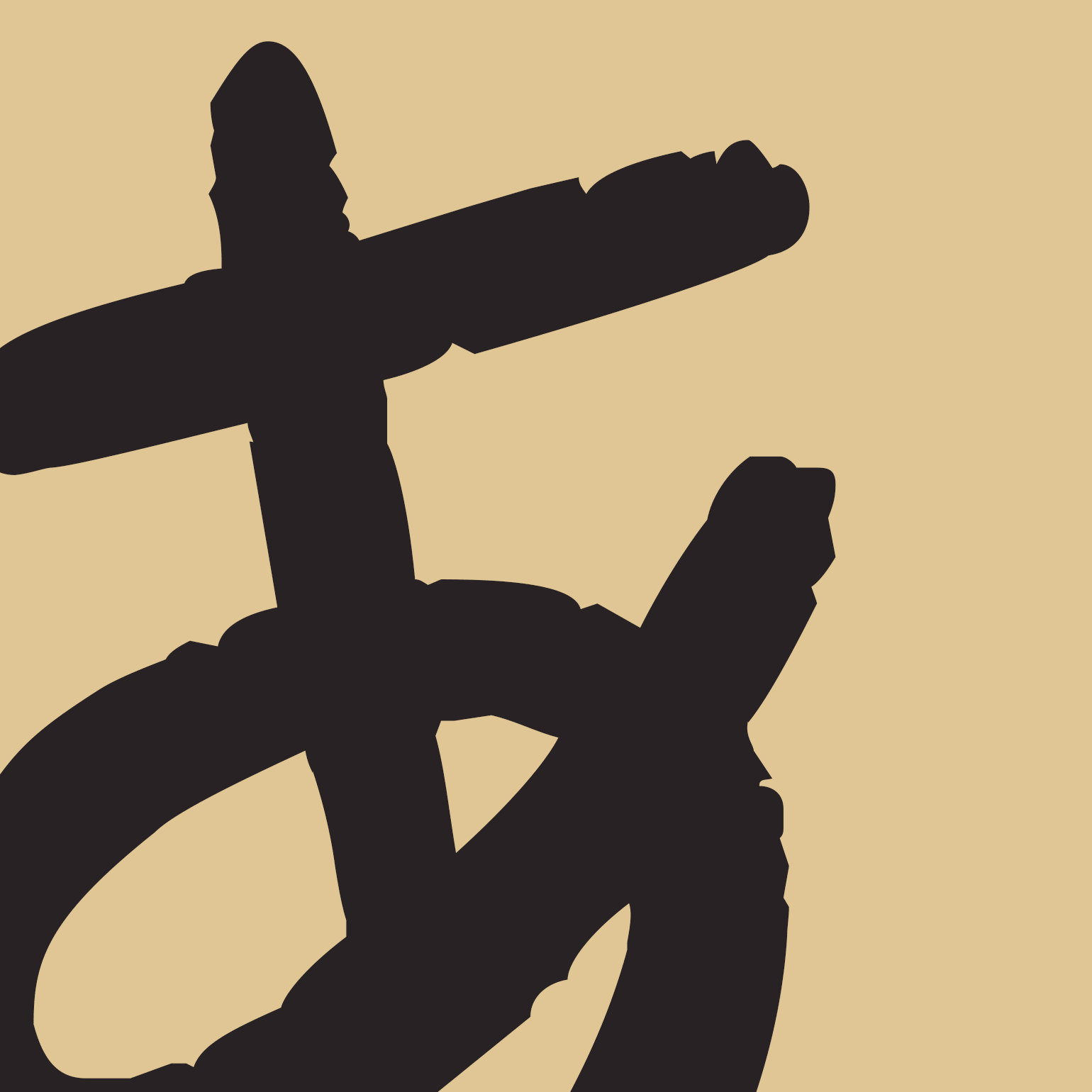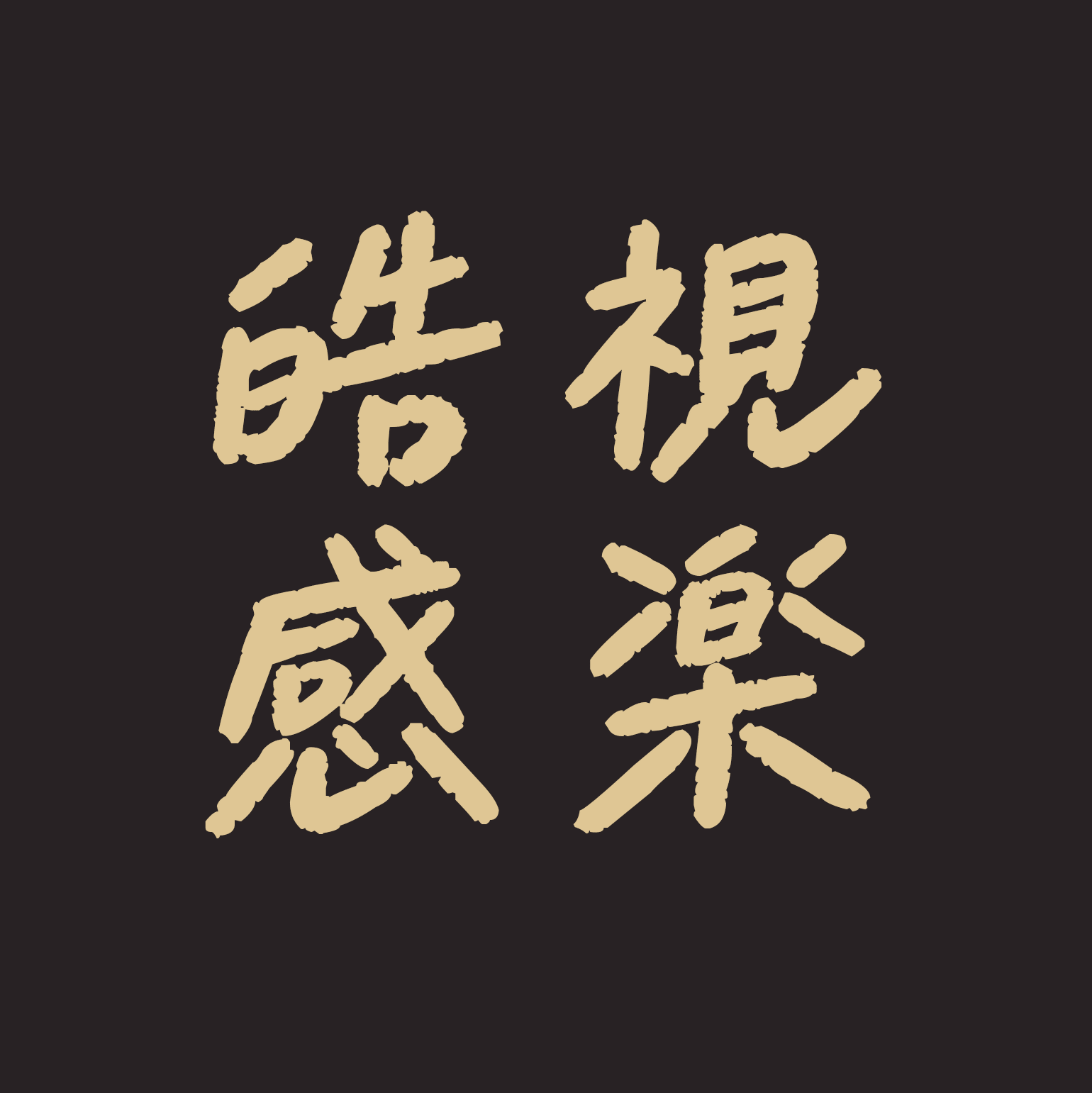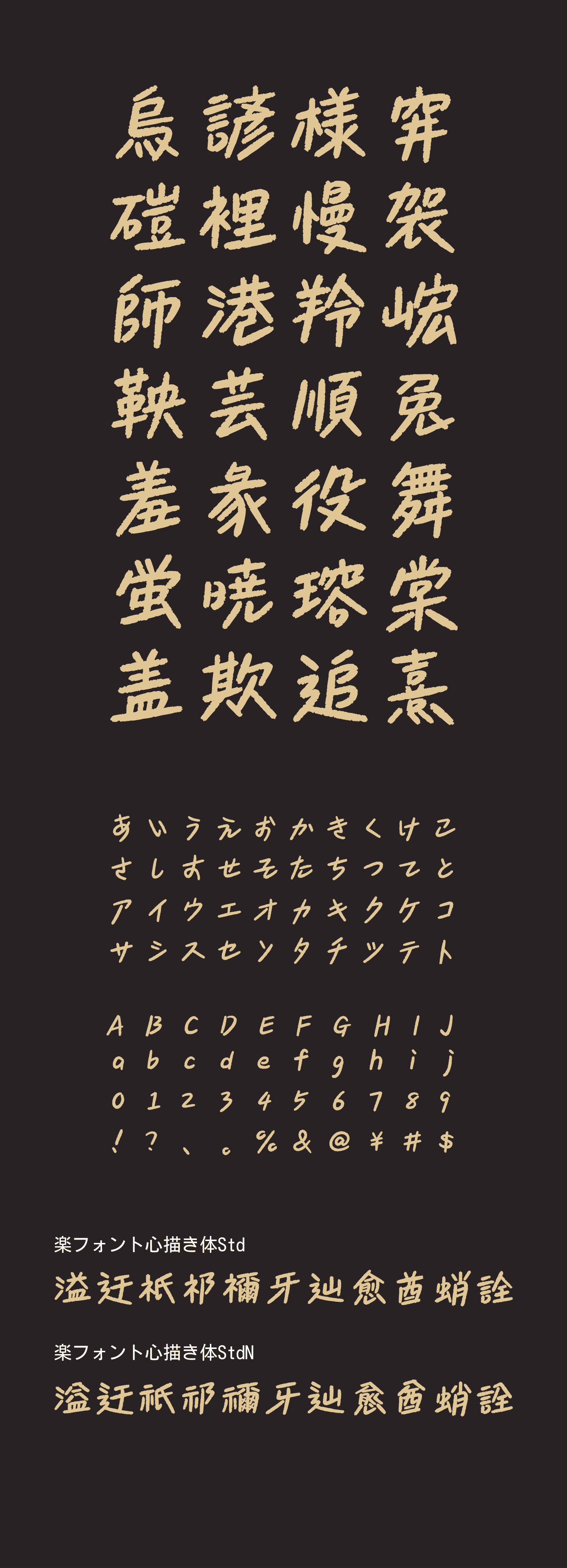
心描き体(こころがきたい)
楽フォント
心描き体(こころがきたい)
清新で自然な雰囲気を持つフォントです。流れるような筆致にブラシの質感を加え、自由で伸びやかな印象を与えます。意図的に引き延ばした点画が、力強さとリズム感を演出します。広告、タイトル、説明文、映画字幕など、多様なデザイン用途に適しています。